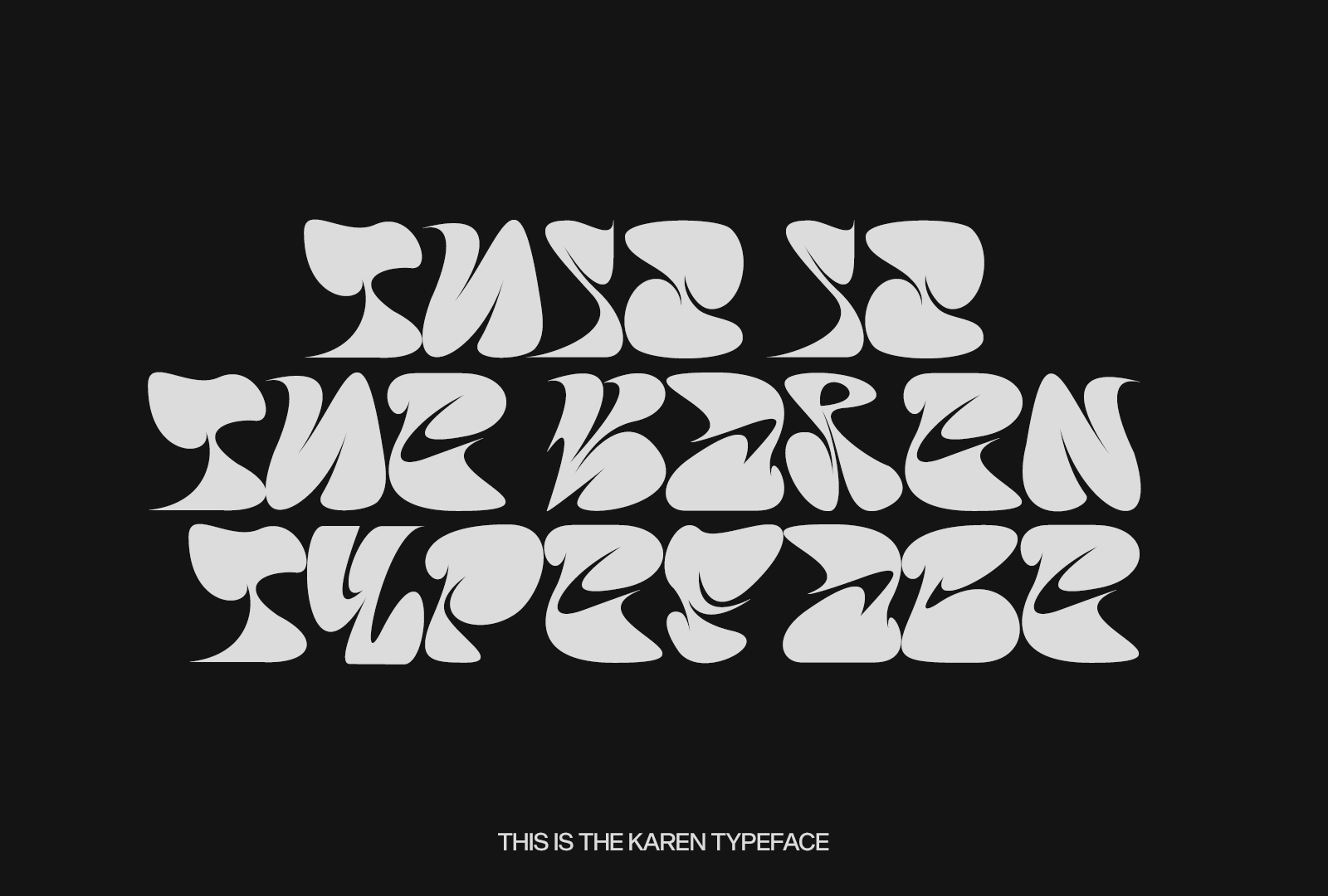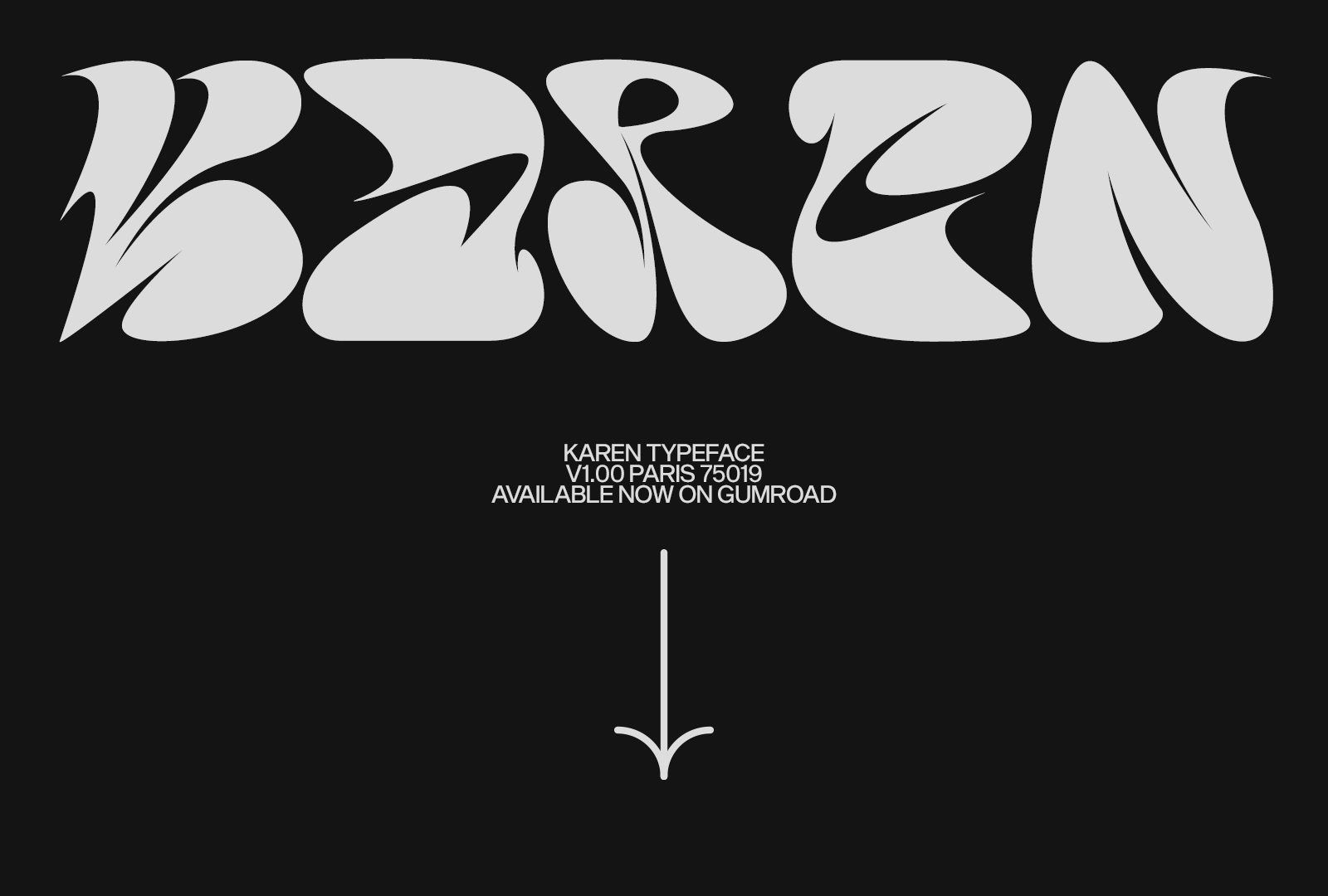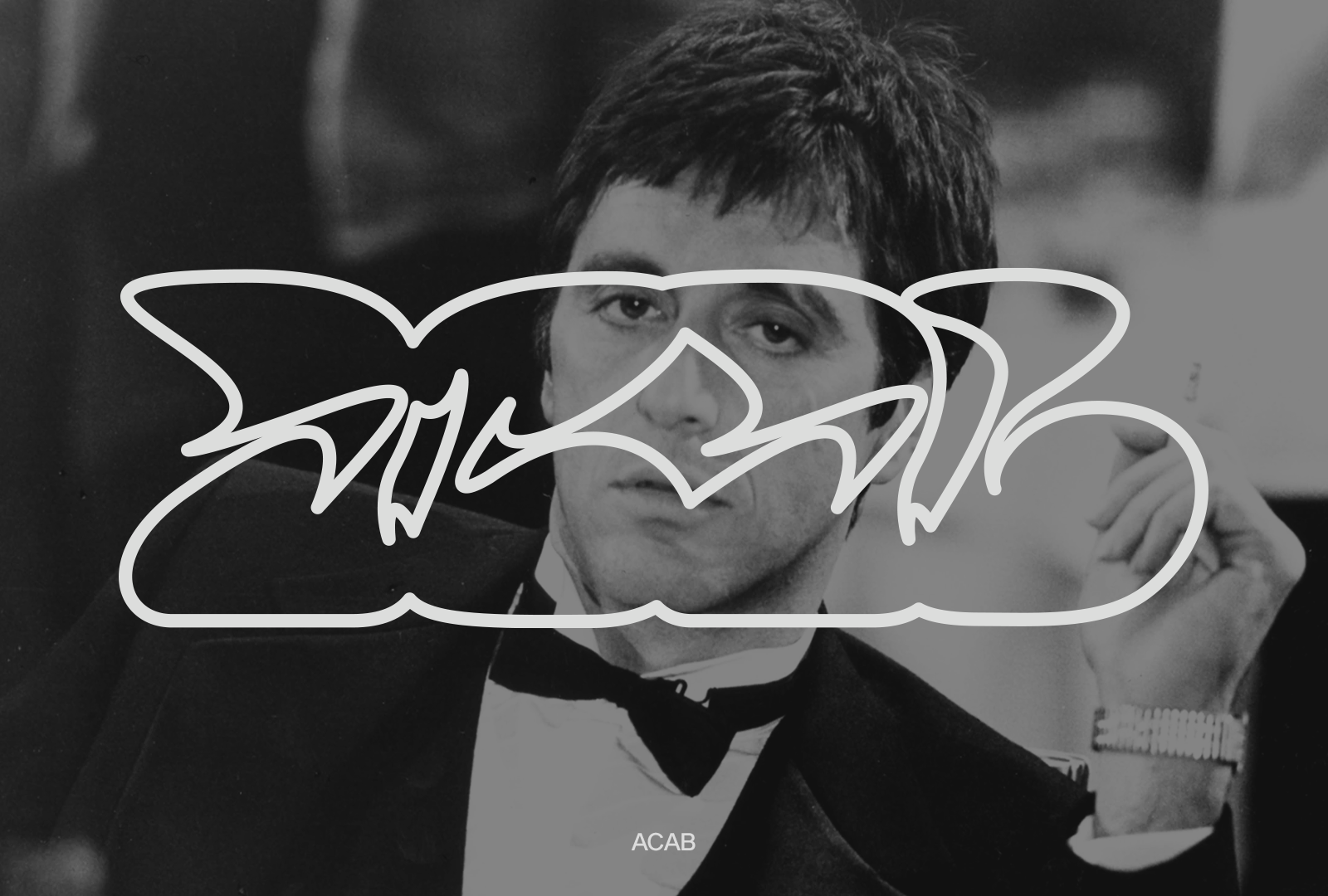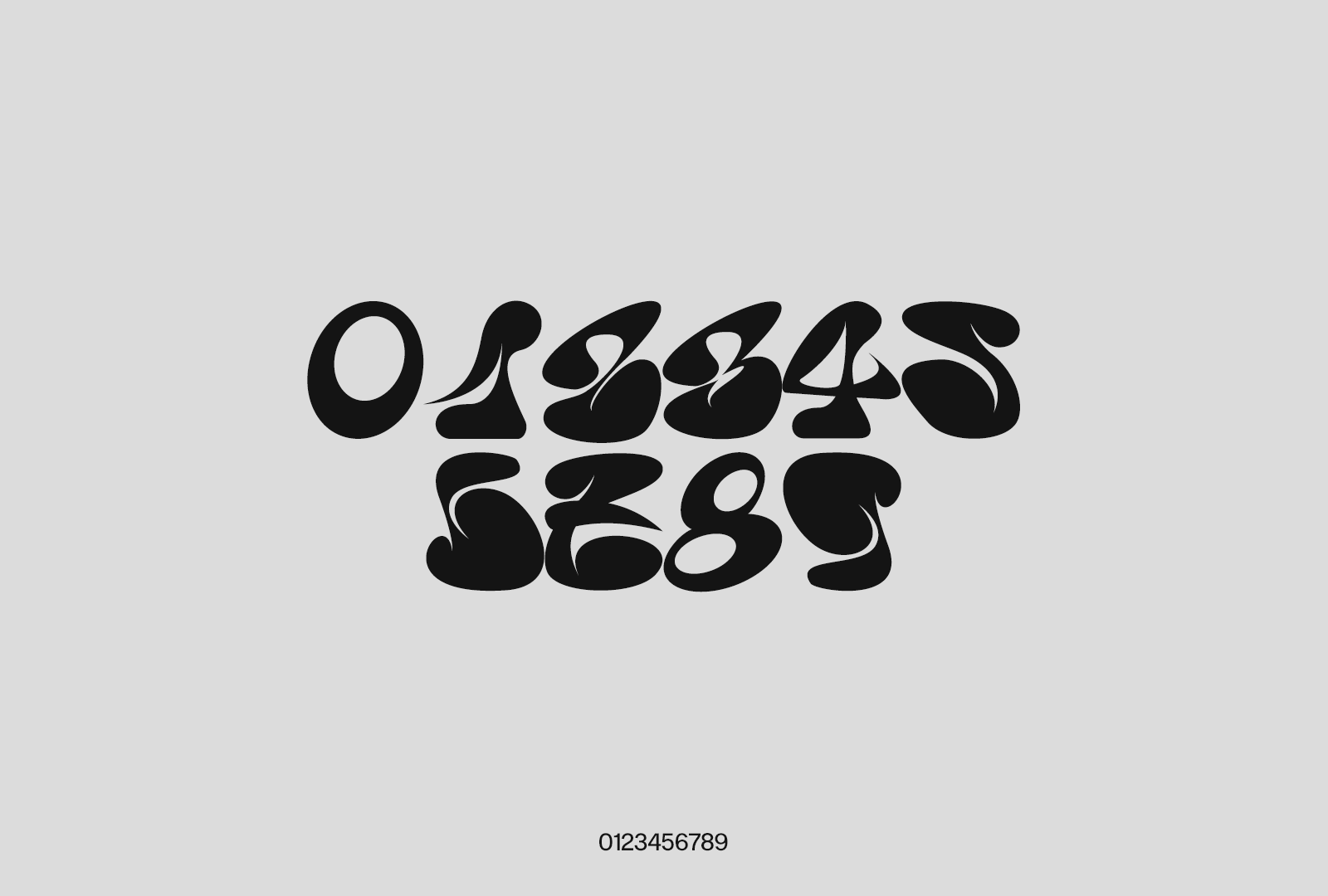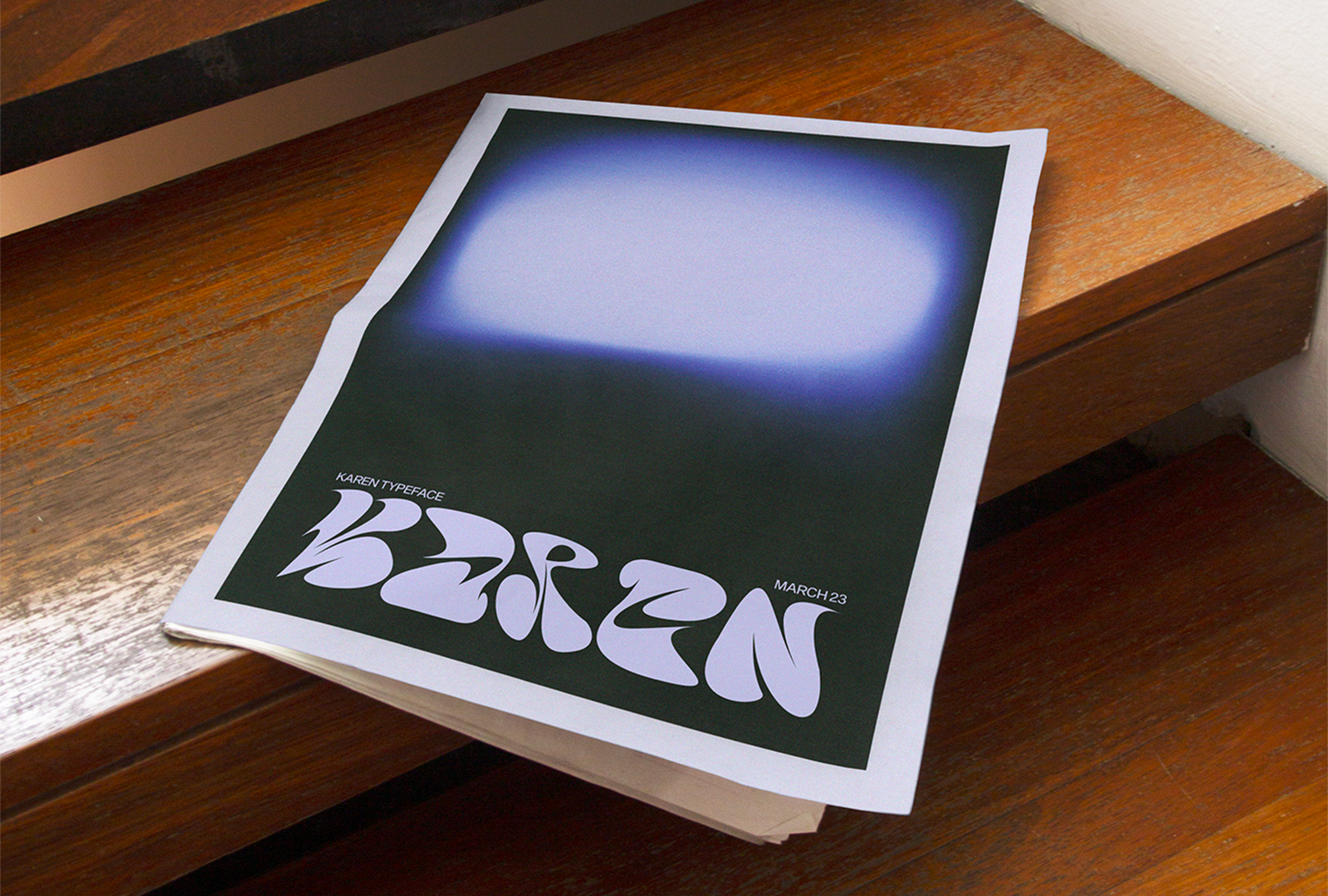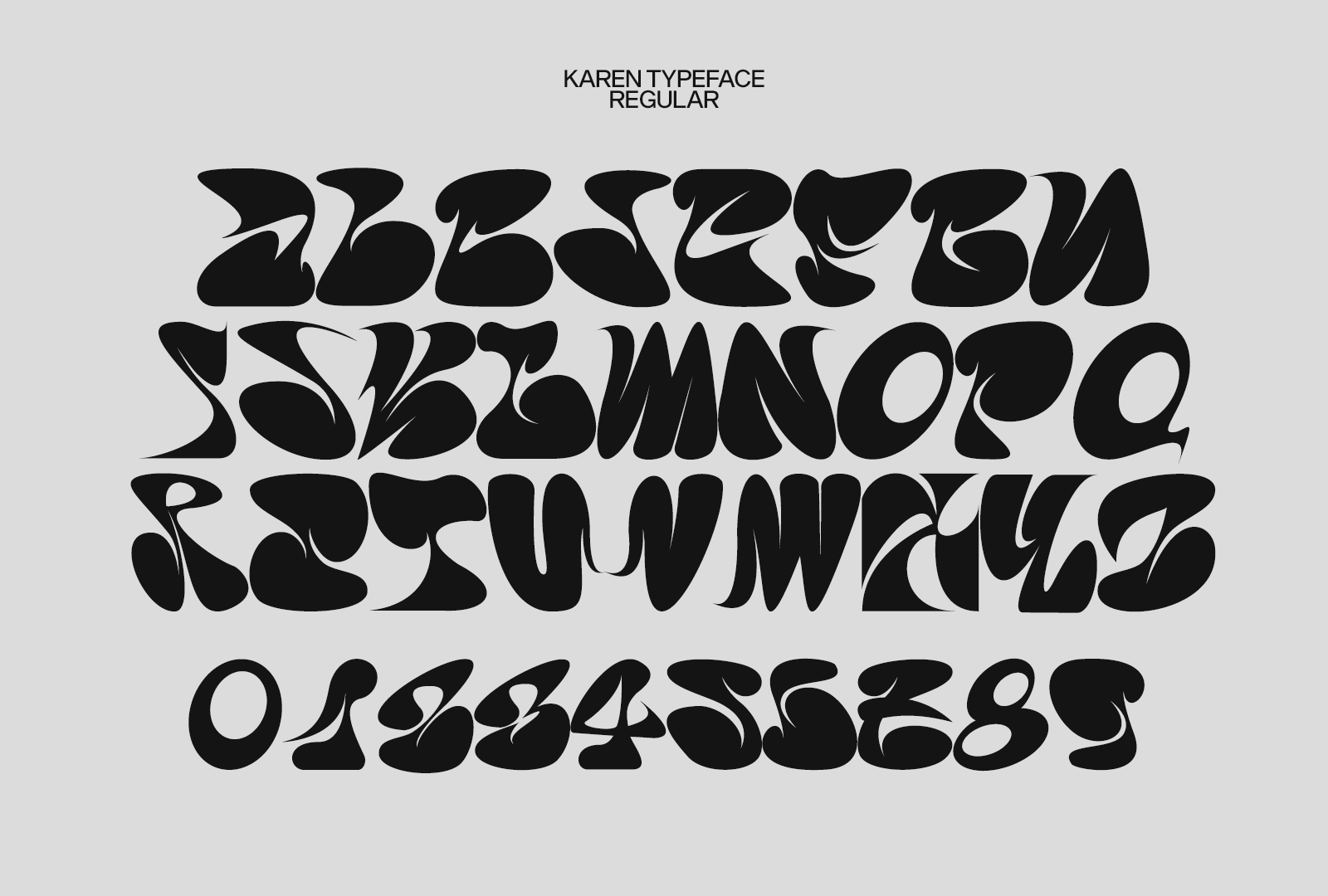
Karen Typeface
Karen Typeface est un caractère d'affichage à une seule casse qui se caractérise par une douce agressivité, des angles vifs et des formes arrondies. Karen n'est disponible qu'en une seule graisse dans la V1.0. Le caractère contient 74 glyphes, dont des lettres, des chiffres et des signes de ponctuation, et supporte 60 langues.
Karen Typeface
Hugo Rita